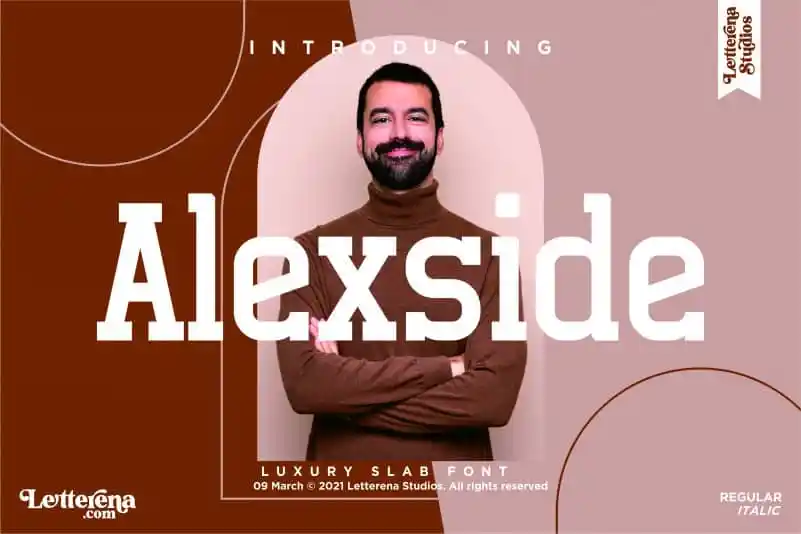
Alexside Slab Font – Fonte Grátis
Alexside Slab Font
Aproveite a oportunidade para imprimir seu próximo projeto gráfico com os detalhes únicos do Alexside Slab Font, uma elegante fonte slab sem serif criada pela Letterenastudios. Com sua tipografia profissional e sofisticada, esta fonte é perfeita para qualquer projeto que exige um toque de luxo, desde o desenho de logotipos a projetos de embalagem de produto. Seja em aplicativos como têxtil homewear ou mesmo em materiais pessoais como cartões de nome, etiquetas e capas de livros, a Alexside Slab garantirá um toque profissional para seu projeto. Ela é perfeitamente adaptada para diversas aplicações, desde o design de marcas até o layout das suas postagens no Instagram, certificando-se que cada detalhe seja visualmente impactante e de alta qualidade. Não hesite em explorar as infinitas possibilidades criativas desta fonte premium para enriquecer seu trabalho gráfico.